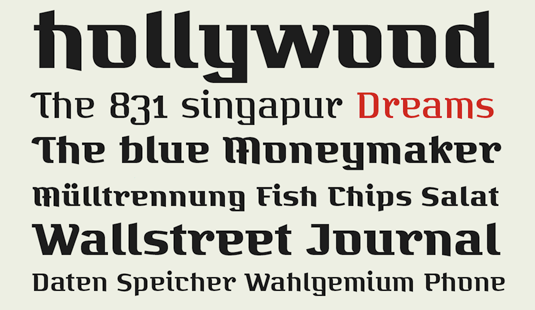
Schrift für indische/österreichisches Reisebüro
ich bin auf der Suche nach einer Schrift für ein indisches "in-coming" Reisebüro mit Sitz in Österreich (Name = Travellounge India). Dieses bietet Individualreisen in geführten Kleingruppen an.
Da ich gerade mit der Entwicklung eines neuen Corporate Designs beschäftigt bin brauche ich eine ansprechende, klare und zeitlose Akzidenzschrift, sowie eine Brotschrift die sich stilistisch dezent von europäischen Erscheinungsbildern abhebt.
Ich habe nach einiger Recherche diese Typographie hier entdeckt und finde Gefallen an ihr. Speziell die geometrische Struktur, die große Varianz der Strichstärken und die Benotung des "a" mit Hilfe eines Querstrichs unterstreichen einen leicht östlichen Charakter. Leider handelt es sich nur um ein Bild, somit kann ich die Schriftart nicht erörtern.
Die PTL Bugis von Verena Gerlach wäre doch was …